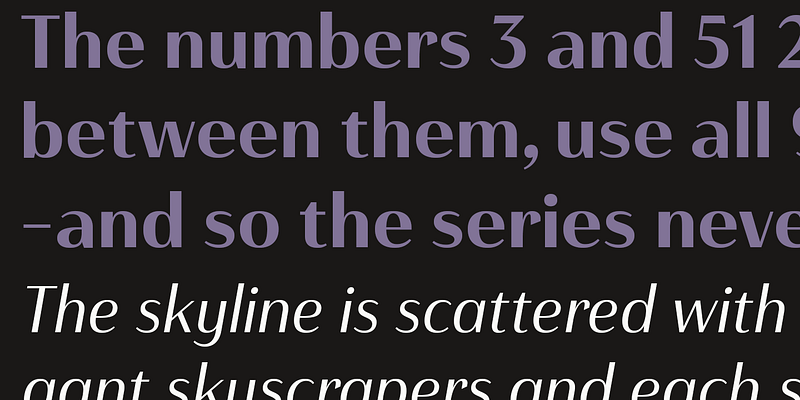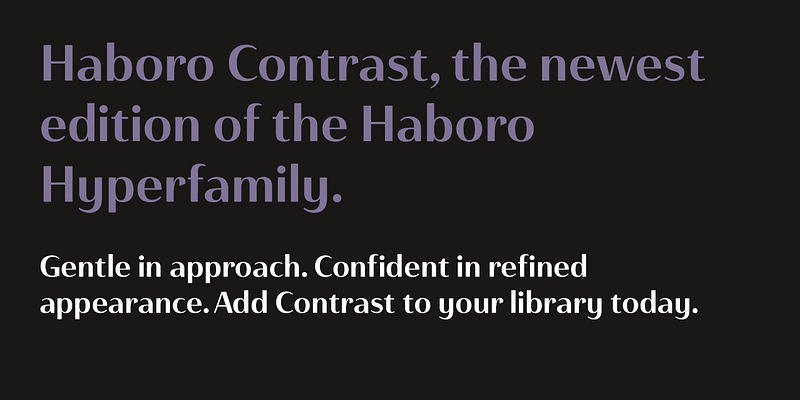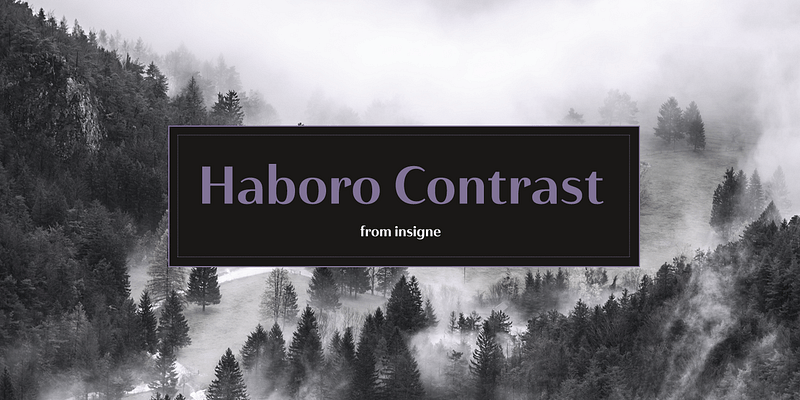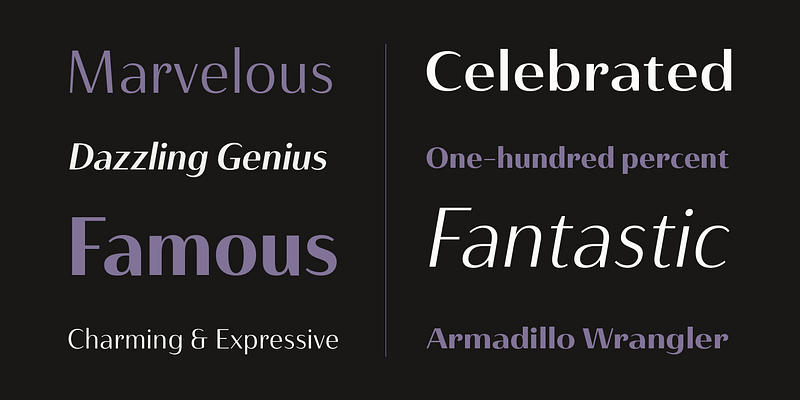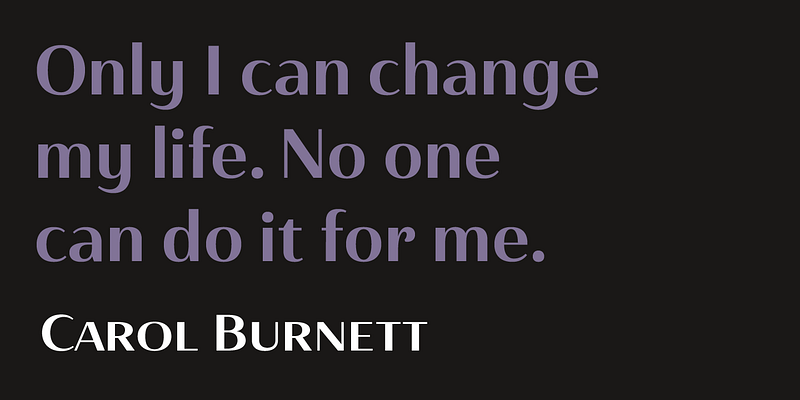
Voici Haboro Contrast, la petite sœur élégante de la grande famille Haboro. Bien que construite à partir des mêmes formes géométriques épurées de Haboro Sans, ce nouvel ajout a été rééquilibré pour des performances élégantes.